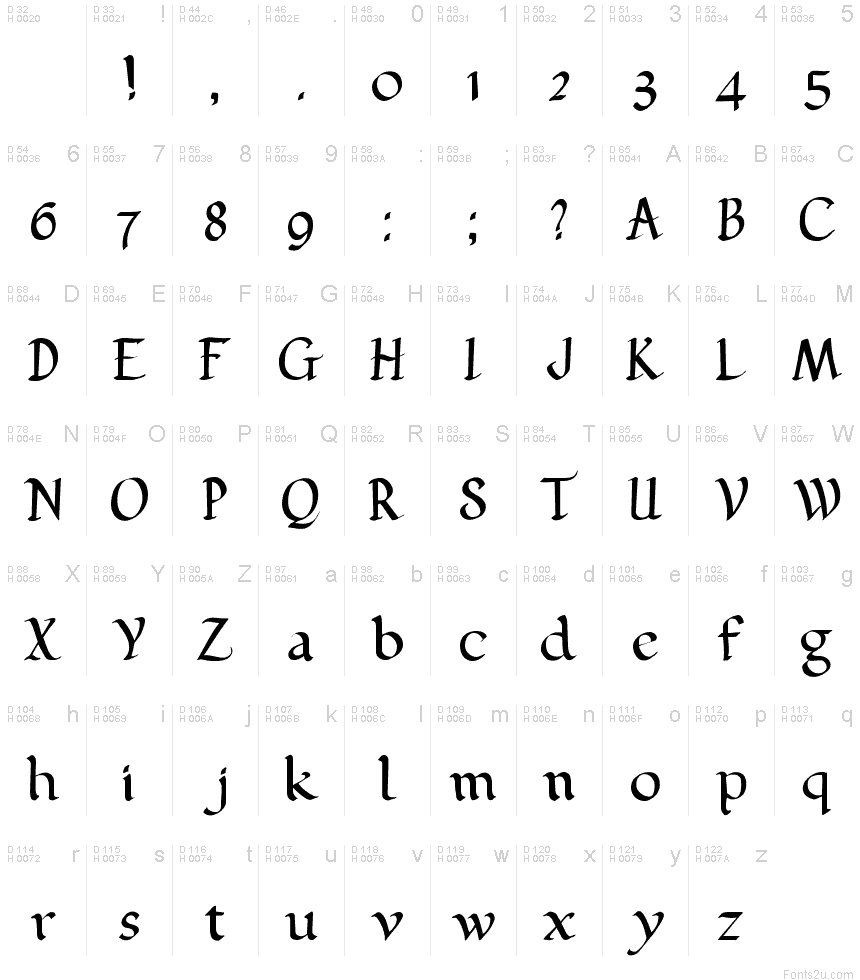
Pehuensito to bezpłatny, wyświetlaczowy krój pisma w stylu retro o łagodnym, baśniowym charakterze. Litery łączą wysokie, nieco ekscentryczne proporcje z zaokrąglonymi, klinowatymi szeryfami i płynnymi krzywiznami, dzięki czemu całość wydaje się staromodna, ale w żaden sposób nie sztywna ani formalna.
Świetnie sprawdza się w identyfikacji wizualnej kawiarni, na okładkach książek, plakatach, opakowaniach i w cytatach redakcyjnych, gdzie nuta nostalgii pomaga nadać odpowiedni ton. Jako darmowy font, idealnie nadaje się również do krótkich nagłówków, plansz tytułowych i znaków logotypowych – długie pionowe pociągnięcia i delikatnie nabrzmiałe krzywizny nadają nawet kilku literom wyrazisty, ręcznie wykonany rytm.